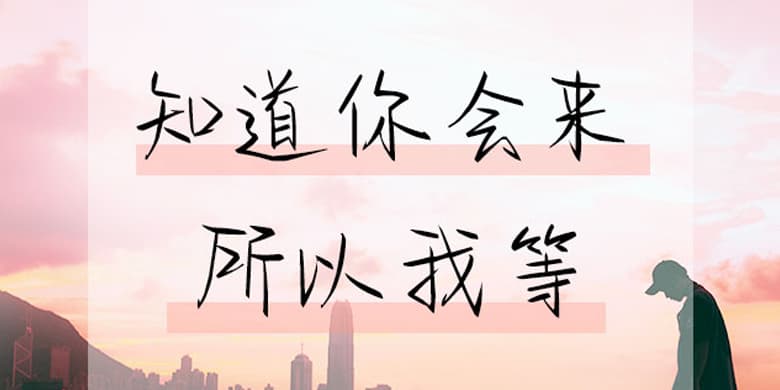
品牌:方正手迹设计师:宋昱东发行时间:2020字库编码:大陆简体(GB2312-80)分类:常规书写·硬笔字体属性:精品字
知道你会来所以我等是一款苍劲有力而又不失文艺的手写体。该字体结构稳定,部分笔画的左低右高给人一种昂扬向上的态度,笔画挺拔有力,随性舒展。该字体适用于文艺类的书刊、品牌广告和产品包装设计,以及社交网络的个性化用字。